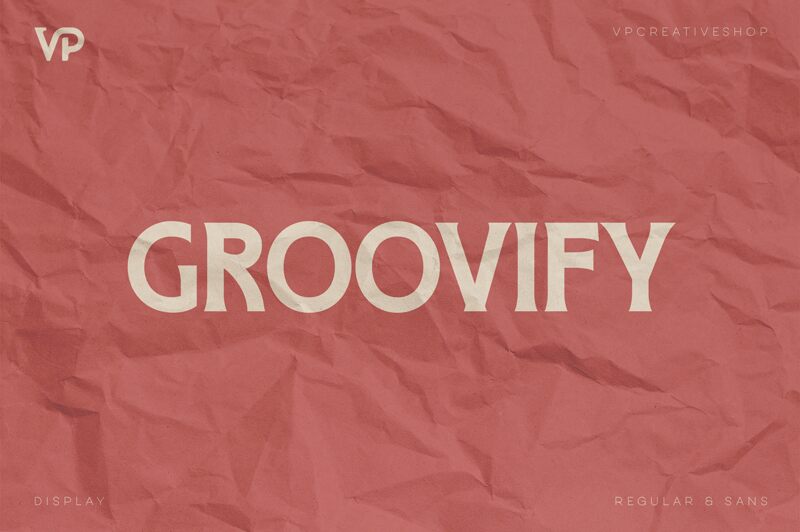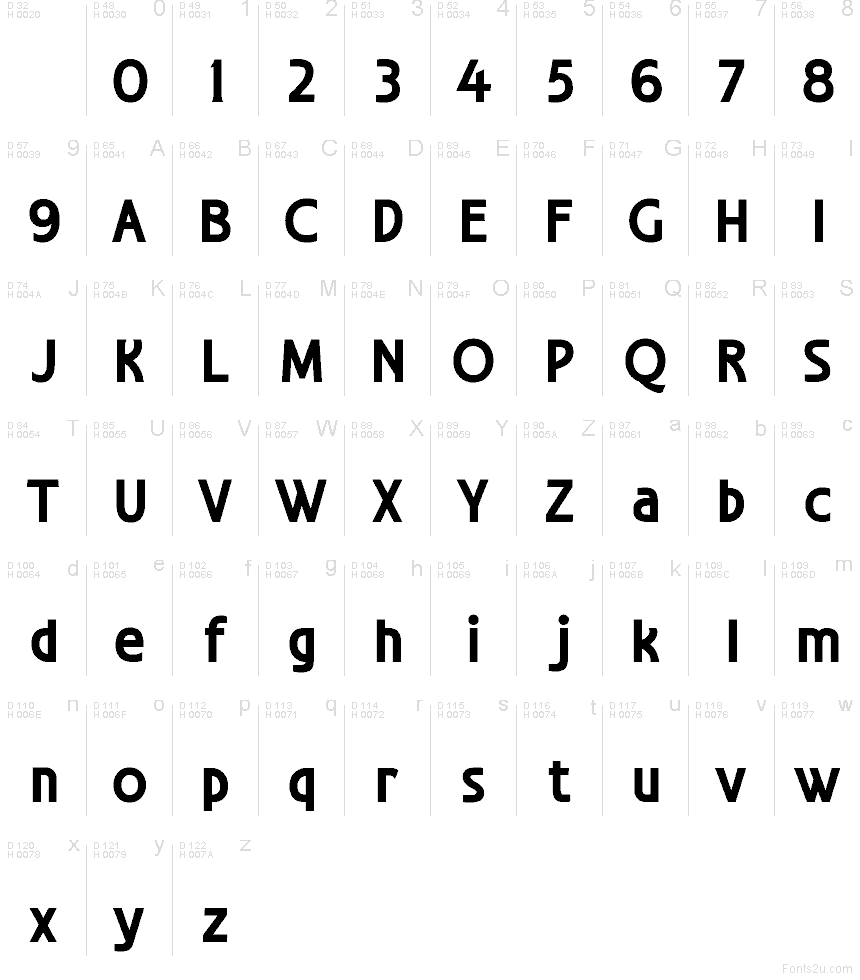
Groovify Demo
Groovify ist eine kostenlose, serifenlose Schriftart mit abgerundeten Formen, die durch großzügige kreisförmige Konturen und eine kompakte, plakative Silhouette besticht. Die beinahe ovalen Formen und fließenden Kurven verleihen dem Schriftbild einen weichen, vollen Rhythmus, während die präzisen Verbindungen verhindern, dass es zu verspielt wirkt.
Diese Balance macht sie zur idealen Wahl für Album-Artworks, Café-Branding, Sticker-Designs, kurze Überschriften und Verpackungen, die eine freundliche und fröhliche Note verlangen. Sie besitzt zudem genügend visuelle Präsenz für Social-Media-Posts und Veranstaltungs-Flyer, bei denen die markanten, abgerundeten Formen das Layout auch ohne zusätzliche Dekoration perfekt tragen.